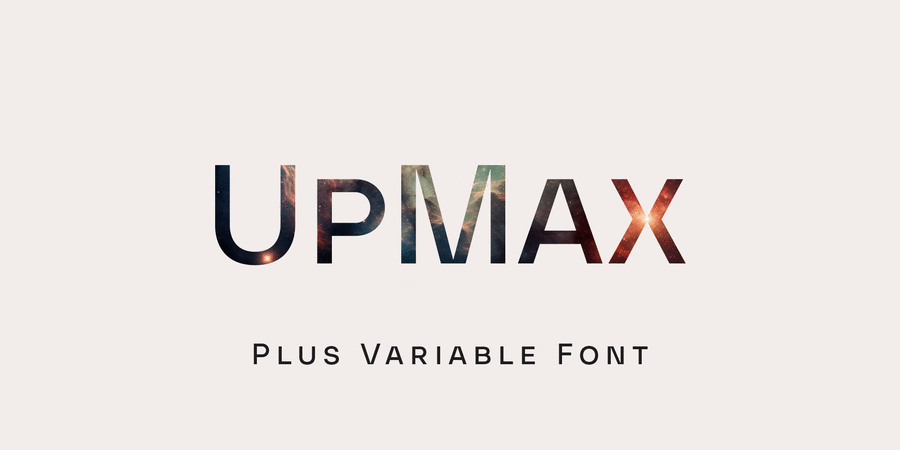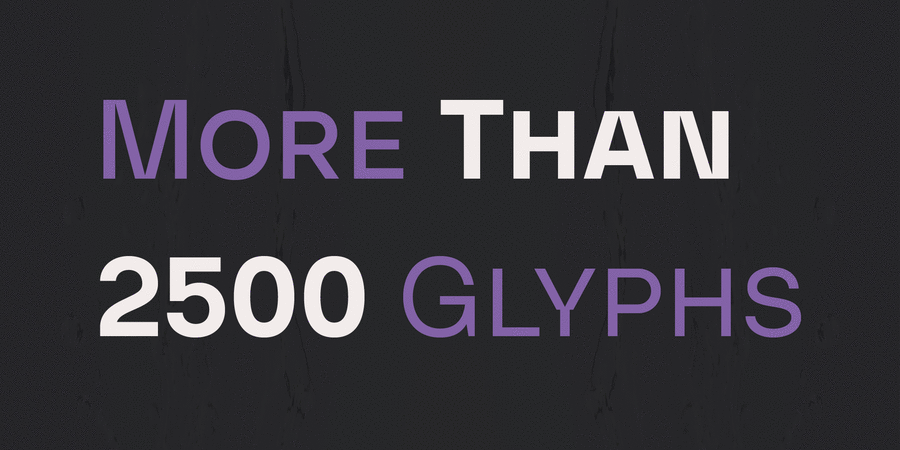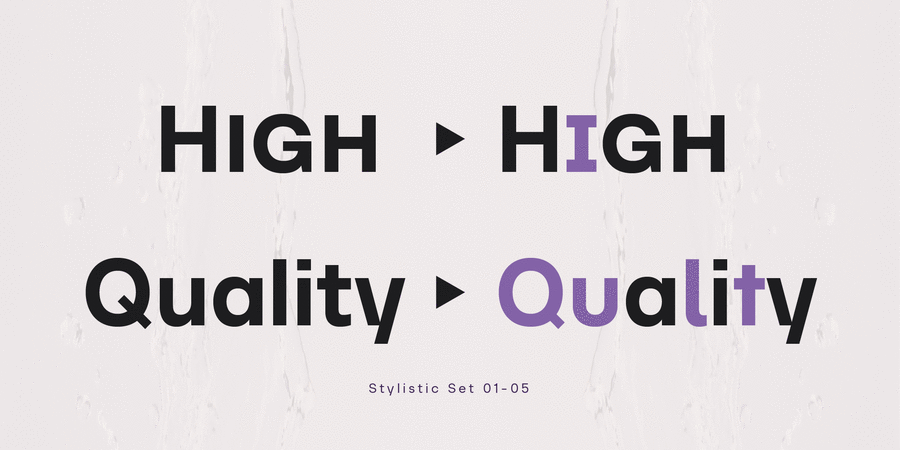
Опис гарнітури UpMaxUpMax — це сучасне сімейство шрифтів. Це сімейство ідеально підходить для графічного дизайну та використання на дисплеях. Підтримка мов: розширена латиниця (включаючи в’єтнамську), кирилицю (включаючи болгарську) та грецьку. Сімейство поставляється в 12 накресленнях, 6 насиченостях і відповідних курсивах. Кожне накреслення включає 2540 гліфів і 36 функцій OpenType (включно з малими заголовними літерами, лігатурами, чисельниками та друкарськими варіантами).
Шрифт розробив Микола Савчук у 2023 році.
Асоціації з сімейством шрифтів UpMaxОсобистість і характер гарнітури:
урбаністичний, зрозумілий, технічний, мінімалістичний, точний, рівний, статичний, нейтральний, твердий, лаконічний, серйозний, впевнений, стійкий, автоматичний, штучний, холодний, машинний, інженерний, міський, чіткий, гострий, креслярський, сучасний, модний, рубаний, тонкий, дротяний, скляний, переконливий, залізний, сталевий, сильний, міцний, індустріальний, техногенний, авторитетний, важливий, солідний, самостійний, відповідальний, добротний, архітектурний, мотивуючий, різкий, робочий, суворий, крутий, амбітний, потужний, жорсткий, значний, квадратний, кондовий, яскравий, помітний, важкий, активний, грубий, гучний, сміливий, нахабний, чорний
хімія, математика, урбаністика, техніка, прилад, код, креслення, конструктор, інженер, автоматика, Місто, наука, дизайн, архітектура, коворкінг, меблі, мода, технології, інновації, девайс, гаджет, ремонт, інструмент, промисловість, машинобудування, завод, взуття, архітектор, склад, тара, будівництво, двигун, верстат, електростанція, енергетика, мотор, Доставка, тренажери, сейф, металургія, сталевар, вантажівка Гарнітура асоціюється з віком: